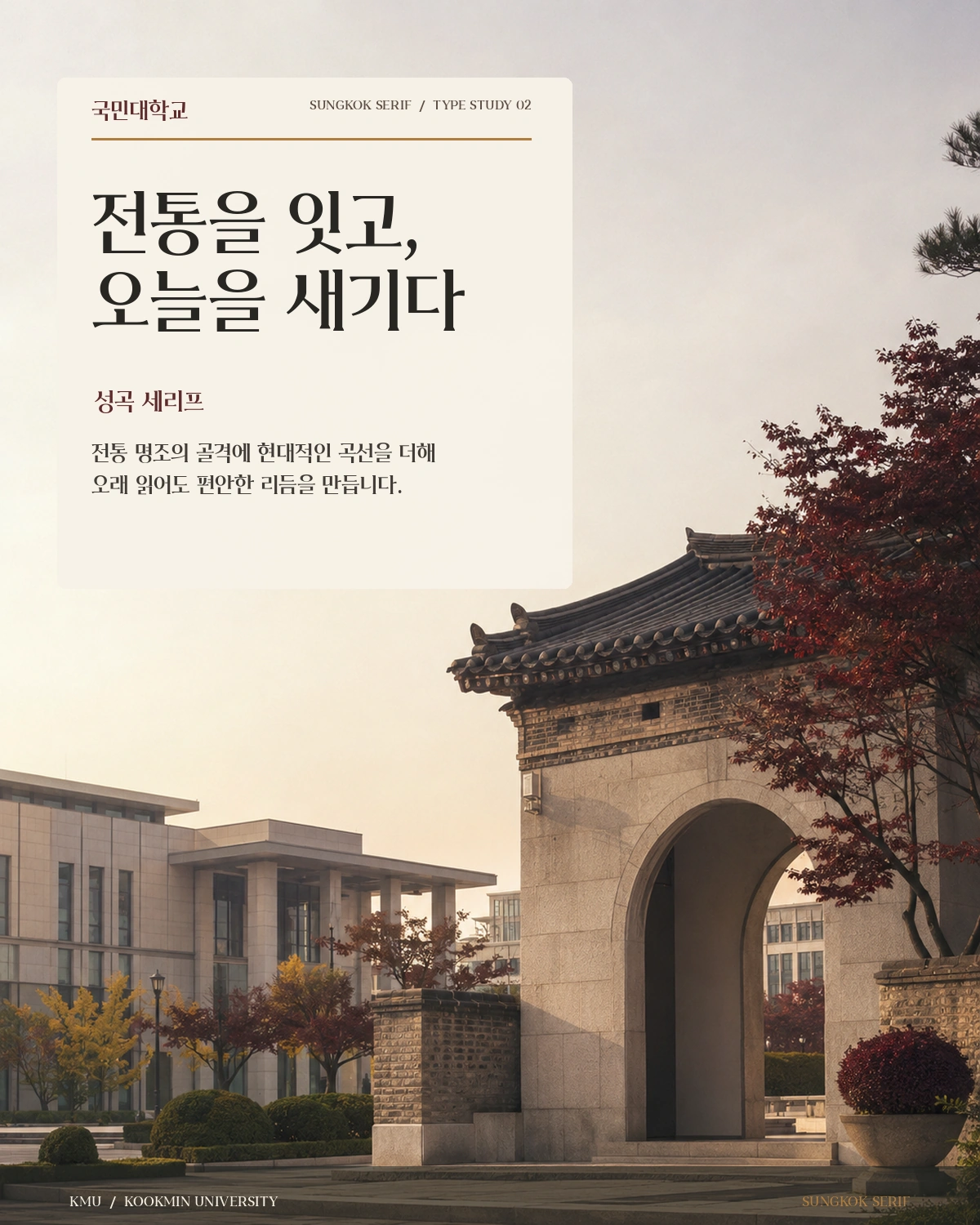
국민대학교 성곡 세리프 — 국민대학교에서 배포하는 무료 폰트입니다. 부리가 있는 전통적인 골격을 가변 폰트 구조로 새로 짜, 전통과 현대를 잇는 세리프 서체
국민대학교가 개교 80주년을 기념해 약 1년에 걸쳐 개발한 전용 서체 가족의 부리 쪽입니다. 이름의 성곡은 국민대의 중흥을 이끈 성곡 김성곤 선생의 호에서 왔고, 창학 정신과 역사성을 상징한다고 밝히고 있습니다.
이 서체 가족의 특징은 구조 자체에 있습니다. 부리가 있는 전통적인 세리프와 부리가 없는 현대적인 산세리프 사이를 오갈 수 있도록 설계됐고, 성곡 세리프와 성곡 세미세리프, 해옹 세미산스, 해옹 산스 네 스타일이 그 스펙트럼을 이룹니다. 이 서체는 그중 부리가 가장 뚜렷한 쪽입니다. 여기에 딩벳 26종이 함께 들어 있습니다.